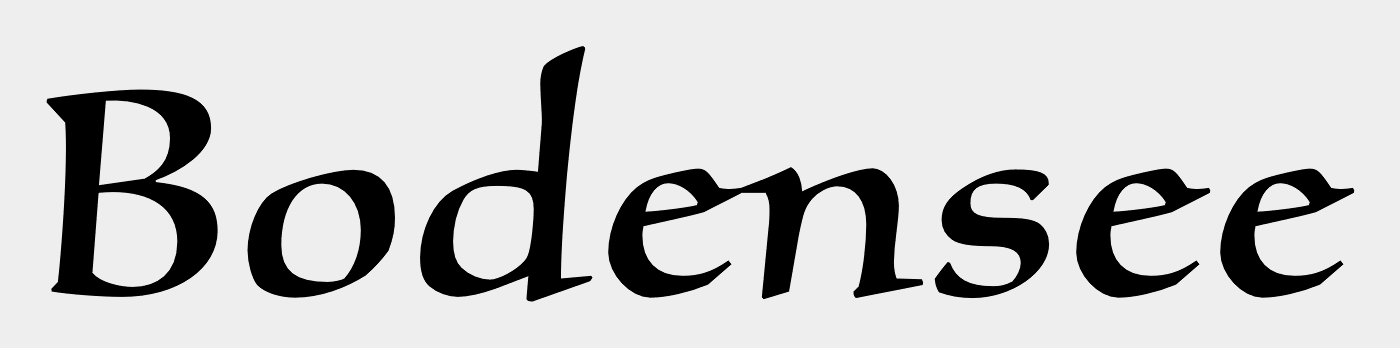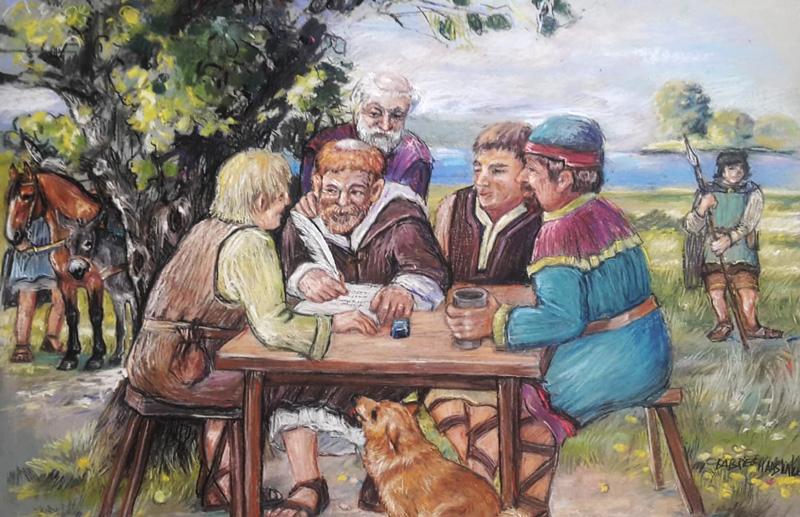
Gut lesbare "Mittelalter-Schrift"
Meine Mutter hat ein mittelalterliches Bild in Pastell gemalt. Es handelt sich dabei um eine Urkunden-Unterzeichnung
irgendwo am Bodensee in der Zeit um 800 herum.
Das Bild soll im Museum des Nachbar-Ortes ausgestellt werden. Es soll ein längerer (ca. A3 oder A4) Begleittext dazu,
der das Bild beschreibt ... Farben, was da passiert auf dem Bild usw.
Nun weiß ich nicht, in welcher Schriftart ich diesen Begleittext setzen soll?
Kriterien wären:
1. Es muss für den Museumsbesucher gut lesbar sein.
2. Es sollte eine mittelalterliche Anmutung in der Schriftart liegen, die evtl auch die Zeit trifft, in der die Urkunde unterzeichnet wurde (ca. 800)
3. Die Schriftart sollte auch noch in etwas kleinerer Schriftgröße funktionieren
Hat denn das Museum bzw. die konkrete Ausstellung keine feste Schrift für alle Fließtexte/Bildunterschriften? Das wäre das übliche.
Es liegt ja weit in der Zeit zurück und damit auch weit von heutigen Satzkonventionen entfernt. Da jetzt einen Mittelalter-Look mitgeben zu wollen, kann schnell so ausgehen wie die klischeehaften Logos von Restaurants mit griechischer/asiatischer/etc. Küche.
ja, du hast natürlich recht, ich werde das mit der "Hausschrift" des Museums in Erfahrung bringen  ...
"längerer Text" und "gut lesbar" beißt sich jetzt aber ein wenig mit den Frauss’schen Fonts.
Klar, es kommt auf die Länge der Texte und die Fläche, die zur Verfügung steht, an. Aber z.B. mit der »Son of Time« ließe sich schon was lesbares mit »MA-Anmutung« erstellen.
Ich würde auf eine gute, lesbare Sans zurückgreifen und diese zu Dekozwecken mit einer Mittelalterschrift™️ kombinieren. Letztere vielleicht für Teaser oder Marginalien. Für 800 n. Chr. könnte eine Karolingische Minuskel, Unziale oder Halbunziale passen.
Ich denke alles in der "Son of Time" zu setzen würde den nicht-typo-affinen Betrachter evtl. überfordern.
Sollte es keine Hausschrift geben, werde ich wie Schnitzel vorgeschlagen hat eine Sans für den Fließtext,
und dann eine "Carolina" / "Silentium" esqe Schrift für die Deko verwenden ... aber jetzt wart ich erst mal ab,
was das Museum so sagt ...